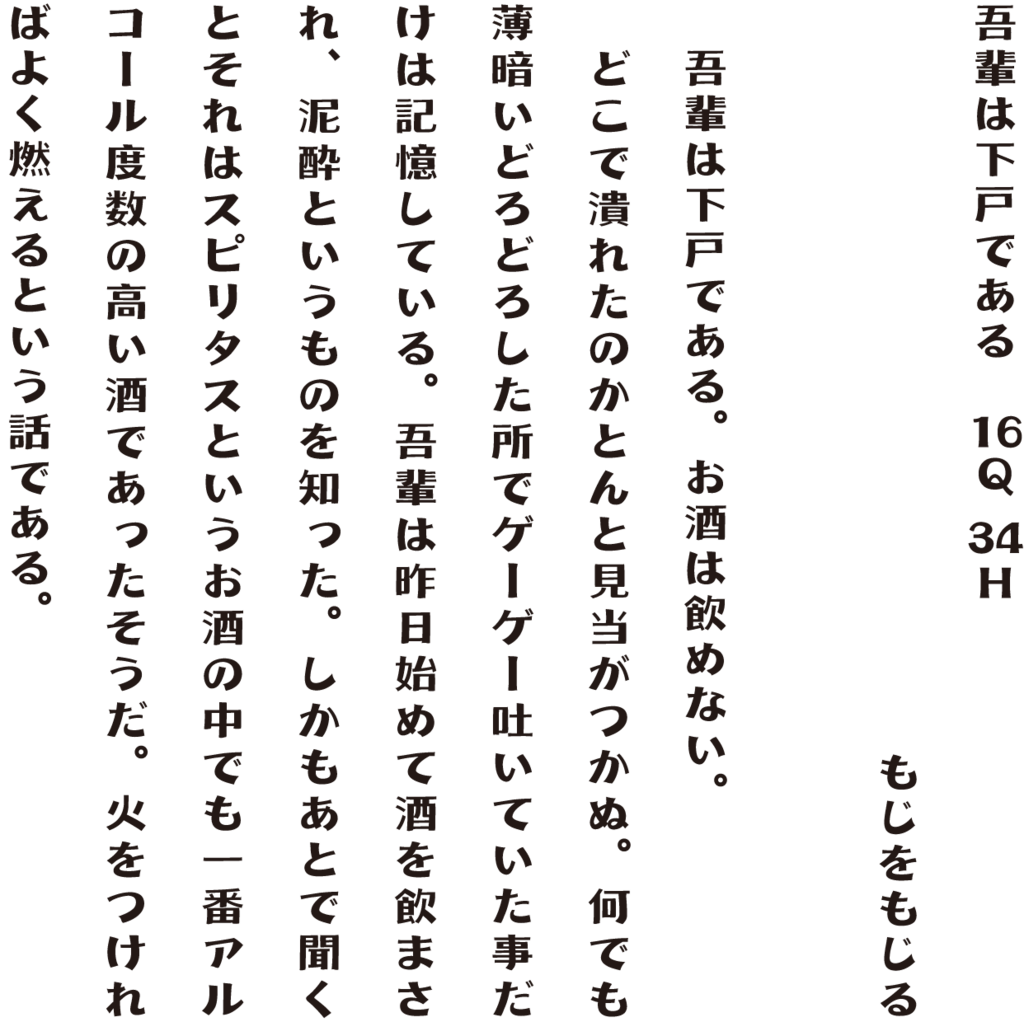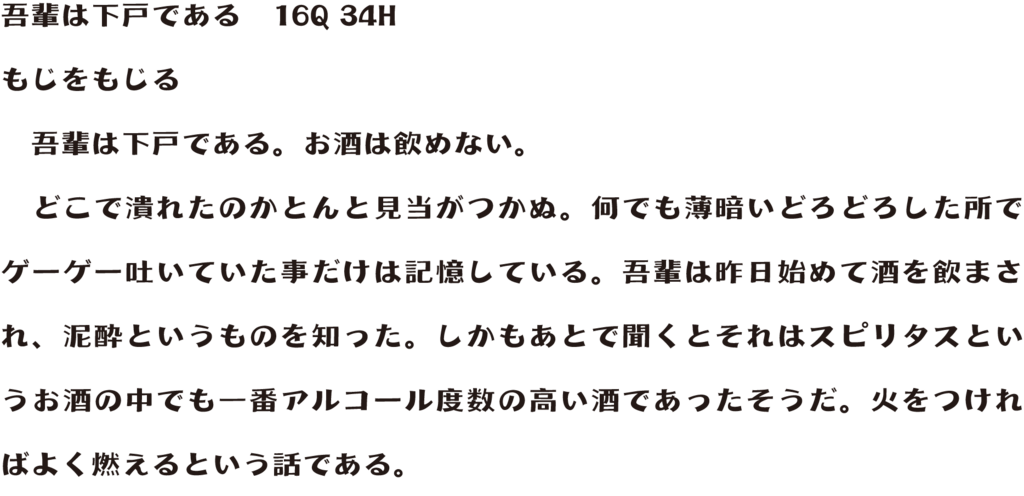
琺瑯看板体
円盤録音機で再生した黒い円盤のイメージと琺瑯看板文字をヒントに昭和の文字印象を応用したレトロ間あふれる書体。太い縦画を中心に細い横画、はらいを加え、全体的にバランスを取っている。
琺瑯看板(ホーロー看板)
琺瑯看板(ホーロー看板)は、主に屋外用の表示として使用される看板の一種で、光沢のある塗装ないし印刷で仕上げられた金属製のものを意味している。1888年から1889年ごろに誕生したとされ、明治・大正・昭和中期まで商品宣伝手法の主流として一時代を築いていたが、商品サイクルの加速化や住宅事情、新聞やテレビ等のメディアの発達に伴い、1975年頃から消えていった。
琺瑯看板体の組見本